เลือกฟอนต์ผิด ชีวิตเปลี่ยน! จิตวิทยาฟอนต์สร้างแบรนด์
การออกแบบตัวอักษรหรือฟอนต์ที่ใช้ในการสื่อสารของแบรนด์ ไม่ว่าจะเป็นบนโลโก้ ฉลากสินค้า หรือสื่อโฆษณาต่างๆ มีอิทธิพลต่อการรับรู้และอารมณ์ของผู้บริโภคมากกว่าที่คิด การทำความเข้าใจในหัวข้อ เลือกฟอนต์ผิด ชีวิตเปลี่ยน! จิตวิทยาฟอนต์สร้างแบรนด์ จึงเป็นกุญแจสำคัญในการสร้างภาพลักษณ์ที่แข็งแกร่งและสื่อสารไปยังกลุ่มเป้าหมายได้อย่างมีประสิทธิภาพ
ประเด็นสำคัญที่ต้องรู้เกี่ยวกับจิตวิทยาฟอนต์
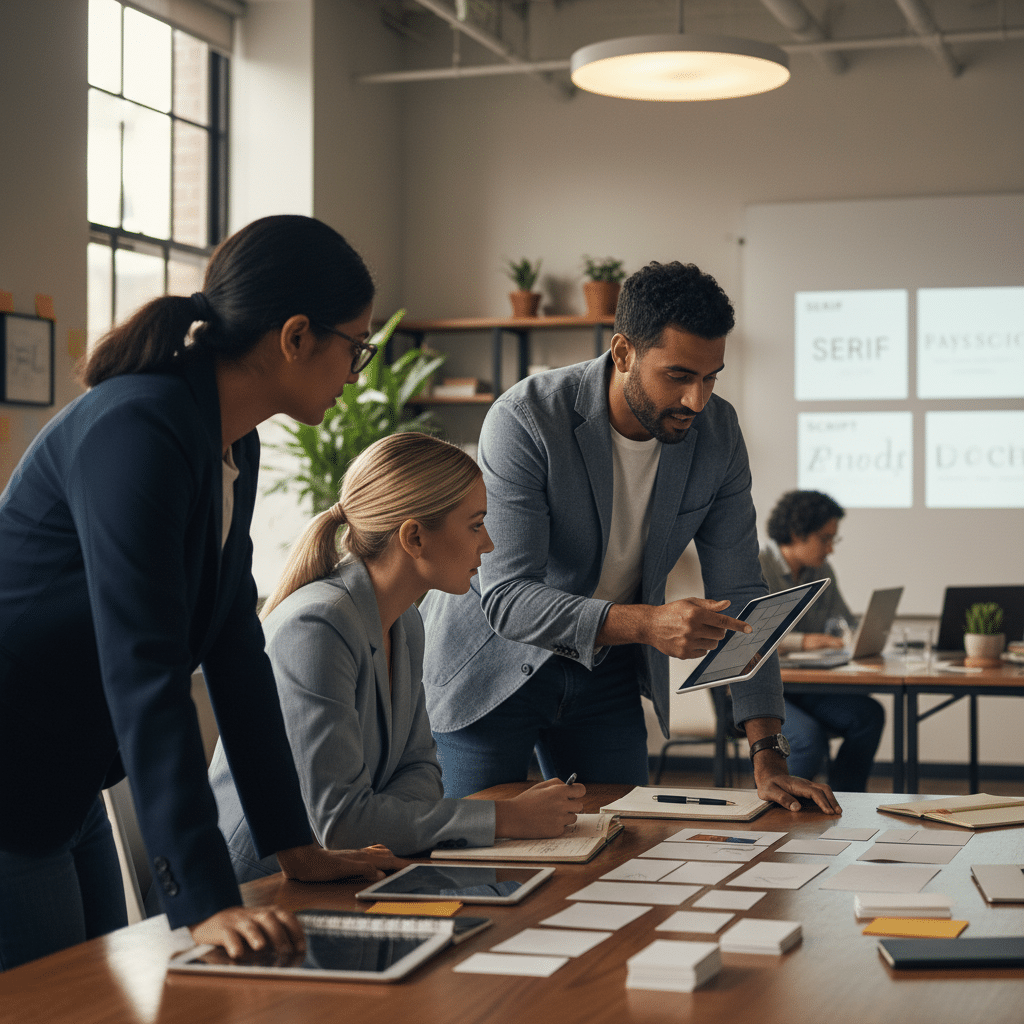
- ฟอนต์แต่ละประเภทสามารถกระตุ้นการรับรู้และอารมณ์ที่แตกต่างกัน เช่น ความน่าเชื่อถือ ความหรูหรา หรือความเป็นมิตร
- การเลือกฟอนต์ที่ไม่สอดคล้องกับบุคลิกของแบรนด์ อาจทำให้การสื่อสารคลาดเคลื่อน ลดความน่าเชื่อถือ และส่งผลเสียต่อภาพลักษณ์โดยรวม
- จิตวิทยาฟอนต์ (Font Psychology) คือการจับคู่คุณลักษณะของฟอนต์ให้เข้ากับเป้าหมายการสื่อสารของแบรนด์ เพื่อสร้างการจดจำและอิทธิพลต่อการตัดสินใจของผู้บริโภค
- ฟอนต์ถือเป็นองค์ประกอบสำคัญเทียบเท่ากับโลโก้และสีประจำแบรนด์ ซึ่งต้องมีความสม่ำเสมอในการใช้งานทุกช่องทาง
- การเลือกฟอนต์สำหรับธุรกิจ SME ควรคำนึงถึงความอ่านง่าย (Legibility) และความสามารถในการปรับใช้กับสื่อหลากหลายประเภท ตั้งแต่ฉลากสินค้าขนาดเล็กไปจนถึงป้ายโฆษณาขนาดใหญ่
ความหมายที่ซ่อนอยู่ในตัวอักษร
ในโลกของการตลาดและการสร้างแบรนด์ ทุกองค์ประกอบภาพล้วนมีความสำคัญในการสื่อสารไปยังผู้บริโภค ตั้งแต่สี โลโก้ ไปจนถึงสิ่งที่มักถูกมองข้ามอย่าง “ฟอนต์” หรือรูปแบบตัวอักษร แต่แท้จริงแล้ว ฟอนต์คือเครื่องมือทรงพลังที่สามารถกำหนดโทนและบุคลิกของแบรนด์ได้ทันทีที่ผู้คนมองเห็น การเลือกฟอนต์ที่เหมาะสมจึงไม่ใช่แค่เรื่องของความสวยงาม แต่เป็นศาสตร์และศิลป์ที่อิงหลักจิตวิทยาเพื่อสร้างการเชื่อมต่อทางอารมณ์กับลูกค้า
จิตวิทยาฟอนต์คืออะไรและเหตุใดจึงสำคัญต่อแบรนด์
นิยามของจิตวิทยาฟอนต์
จิตวิทยาฟอนต์ (Font Psychology) คือการศึกษาว่ารูปแบบตัวอักษรที่แตกต่างกันส่งผลต่อความคิด ความรู้สึก และการรับรู้ของผู้คนอย่างไร ในเชิงการตลาด นี่คือกระบวนการเลือกใช้ฟอนต์อย่างมีกลยุทธ์ เพื่อให้สอดคล้องกับบุคลิกภาพของแบรนด์ (Brand Personality) และกระตุ้นการตอบสนองที่ต้องการจากกลุ่มเป้าหมาย ไม่ว่าจะเป็นการสร้างความน่าเชื่อถือ ความรู้สึกหรูหรา ความเป็นมิตร หรือความทันสมัย
ฟอนต์ทำหน้าที่เป็นเหมือน “น้ำเสียง” ของแบรนด์ในรูปแบบภาพ แม้ว่าข้อความจะเหมือนกัน แต่การนำเสนอด้วยฟอนต์ที่ต่างกันสามารถเปลี่ยนการตีความของผู้รับสารได้อย่างสิ้นเชิง ตัวอย่างเช่น ฟอนต์ที่ดูสนุกสนานอาจไม่เหมาะกับสถาบันการเงินที่ต้องการความน่าเชื่อถือ ในทางกลับกัน ฟอนต์ที่ดูเป็นทางการเกินไปก็อาจทำให้แบรนด์สินค้าสำหรับเด็กดูไม่น่าเข้าถึง
พลังของฟอนต์ในการสื่อสารอัตลักษณ์แบรนด์
ฟอนต์เป็นส่วนหนึ่งของอัตลักษณ์แบรนด์ (Brand Identity) ที่มีความสำคัญไม่แพ้โลโก้หรือสี การเลือกฟอนต์ที่สอดคล้องกันในทุกสื่อ ไม่ว่าจะเป็นเว็บไซต์ บรรจุภัณฑ์ หรือสื่อสังคมออนไลน์ จะช่วยสร้างความแข็งแกร่งและการจดจำแบรนด์ได้ในระยะยาว งานวิจัยเชิงการตลาดบางชิ้นชี้ให้เห็นว่าฟอนต์บางประเภทสามารถเพิ่มการรับรู้ในคุณลักษณะบางอย่างของแบรนด์ได้จริง เช่น เพิ่มความน่าเชื่อถือ หรือสร้างความโดดเด่นในใจผู้บริโภคได้ในระดับที่วัดผลเป็นเปอร์เซ็นต์
การเลือกฟอนต์ที่ไม่สอดคล้องกับโทนของแบรนด์ อาจทำให้ผู้รับสารเกิดความสับสน ลดการมีส่วนร่วม และบั่นทอนความน่าเชื่อถือของแบรนด์ลงอย่างไม่น่าเชื่อ
ดังนั้น สำหรับผู้ประกอบการ SME การให้ความสำคัญกับการเลือกฟอนต์ตั้งแต่ขั้นตอนการออกแบบโลโก้ หรือออกแบบฉลากสินค้า จึงเป็นการลงทุนที่คุ้มค่าเพื่อสร้างรากฐานของแบรนด์ให้มั่นคง
ถอดรหัสบุคลิกภาพผ่านประเภทฟอนต์
การทำความเข้าใจประเภทของฟอนต์และบุคลิกภาพที่แต่ละประเภทสื่อออกมา จะช่วยให้การเลือกฟอนต์สำหรับสร้างแบรนด์เป็นไปอย่างแม่นยำและตรงเป้าหมายมากขึ้น โดยฟอนต์สามารถแบ่งออกเป็นกลุ่มหลักๆ ได้ดังนี้
| ประเภทฟอนต์ | บุคลิกภาพและการรับรู้ | เหมาะสำหรับแบรนด์ |
| Serif (มีเชิง) | เป็นทางการ, คลาสสิก, น่าเชื่อถือ, สง่างาม, มีประวัติศาสตร์ | สถาบันการเงิน, สำนักกฎหมาย, แบรนด์หรู, สินค้าที่มีประวัติยาวนาน, สื่อสิ่งพิมพ์, มหาวิทยาลัย |
| Sans-serif (ไม่มีเชิง) | ทันสมัย, เรียบง่าย, เป็นมิตร, เข้าถึงง่าย, ชัดเจน | บริษัทเทคโนโลยี, สตาร์ทอัพ, แบรนด์แฟชั่นสมัยใหม่, ธุรกิจบริการที่เน้นความรวดเร็ว, แอปพลิเคชัน |
| Script (ลายมือ) | หรูหรา, อ่อนหวาน, เป็นส่วนตัว, สร้างสรรค์, โรแมนติก | การ์ดเชิญ, แบรนด์เครื่องสำอาง, ร้านขนม, ร้านอาหาร fine-dining, สินค้าแฮนด์เมด |
| Display / Decorative | สนุกสนาน, มีเอกลักษณ์เฉพาะตัวสูง, ดึงดูดสายตา, ตามสมัยนิยม | โลโก้, หัวข้อโปสเตอร์, แบรนด์สินค้าสำหรับเด็ก, อีเวนต์พิเศษ, สินค้าตามฤดูกาล |
Serif: ความคลาสสิกและความน่าเชื่อถือ
ฟอนต์ประเภท Serif หรือฟอนต์ “มีเชิง” คือฟอนต์ที่มีขีดเล็กๆ ประดับอยู่ที่ปลายตัวอักษร เป็นรูปแบบฟอนต์ที่มีมาแต่ดั้งเดิม ให้ความรู้สึกถึงความมั่นคง, ประวัติศาสตร์, และความน่าเชื่อถือ จึงมักถูกเลือกใช้โดยแบรนด์ที่ต้องการสร้างภาพลักษณ์ที่ดูเป็นทางการและทรงเกียรติ เช่น สถาบันการเงิน, หนังสือพิมพ์, หรือแบรนด์สินค้าหรูหรา
Sans-serif: ความทันสมัยและความเป็นมิตร
“Sans” ในภาษาฝรั่งเศสแปลว่า “ไม่มี” ดังนั้น Sans-serif จึงหมายถึงฟอนต์ที่ “ไม่มีเชิง” ที่ปลายตัวอักษร ทำให้ดูเรียบง่าย, สะอาดตา, และทันสมัย ฟอนต์กลุ่มนี้ได้รับความนิยมอย่างสูงในยุคดิจิทัลเนื่องจากอ่านง่ายบนหน้าจอคอมพิวเตอร์และมือถือ แบรนด์เทคโนโลยี, สตาร์ทอัพ, และธุรกิจที่ต้องการสื่อสารความเรียบง่ายและเป็นมิตรมักจะเลือกใช้ฟอนต์ประเภทนี้ ฟอนต์ Sans-serif ยังสามารถแบ่งย่อยได้อีก เช่น:
- Humanist Sans: ให้ความรู้สึกเป็นกันเองและจริงใจ มีความโค้งมนคล้ายลายมือมนุษย์
- Geometric Sans: สร้างจากรูปทรงเรขาคณิตพื้นฐาน ทำให้ดูเที่ยงตรงและทันสมัย
- Grotesque: เป็นฟอนต์ Sans-serif ยุคแรกๆ ที่มีความคลาสสิกร่วมสมัย ให้ความรู้สึกเรียบง่ายแต่ทรงพลัง
Script & Display: อารมณ์ความรู้สึกและความเฉพาะตัว
ฟอนต์ประเภท Script เลียนแบบลายมือเขียน ให้ความรู้สึกเป็นส่วนตัว, อ่อนหวาน, และหรูหรา เหมาะสำหรับแบรนด์ที่ต้องการเน้นอารมณ์ความรู้สึก เช่น ร้านดอกไม้, การ์ดแต่งงาน, หรือแบรนด์เครื่องสำอาง ส่วนฟอนต์ Display หรือ Decorative เป็นฟอนต์ที่ถูกออกแบบมาให้มีเอกลักษณ์โดดเด่นเพื่อดึงดูดสายตาโดยเฉพาะ มักใช้สำหรับหัวข้อใหญ่ๆ หรือโลโก้ แต่ไม่เหมาะกับเนื้อหาขนาดยาวเพราะอ่านค่อนข้างยาก การใช้ฟอนต์กลุ่มนี้ต้องระมัดระวัง เพราะหากใช้ผิดบริบทอาจทำให้แบรนด์ดูไม่เป็นมืออาชีพได้
แนวทางปฏิบัติในการเลือกฟอนต์เพื่อสร้างแบรนด์ให้แข็งแกร่ง
การเลือกฟอนต์ไม่ใช่การสุ่มเลือกตามความชอบส่วนตัว แต่เป็นกระบวนการที่ต้องวางแผนอย่างเป็นระบบเพื่อให้ได้ผลลัพธ์ที่ดีที่สุด นี่คือแนวทางปฏิบัติที่สามารถนำไปปรับใช้ได้
1. กำหนดเป้าหมายและบุคลิกของแบรนด์ให้ชัดเจน
ก่อนจะเลือกฟอนต์ ต้องตอบคำถามสำคัญเกี่ยวกับแบรนด์ให้ได้ก่อน เช่น แบรนด์ต้องการสื่อสารอะไร? (ความน่าเชื่อถือ, ความสนุกสนาน, ความหรูหรา) กลุ่มเป้าหมายคือใคร? บุคลิกของแบรนด์เป็นอย่างไร? (จริงจัง, เป็นกันเอง, ทันสมัย) เมื่อมีภาพที่ชัดเจนแล้ว การเลือกประเภทฟอนต์ที่สอดคล้องกับบุคลิกเหล่านั้นจะทำได้ง่ายขึ้น
2. คำนึงถึงความอ่านง่ายและการใช้งานในหลายแพลตฟอร์ม
ความสวยงามต้องมาพร้อมกับประโยชน์ใช้สอย ฟอนต์ที่เลือกต้องอ่านง่าย (Legible) ในทุกขนาด ไม่ว่าจะอยู่บนฉลากสินค้าชิ้นเล็กๆ, เมนูอาหาร, เว็บไซต์บนมือถือ, หรือป้ายโฆษณาขนาดใหญ่ ควรทดสอบฟอนต์ในสถานการณ์การใช้งานจริงเพื่อให้แน่ใจว่าข้อความยังคงสื่อสารได้อย่างชัดเจน
3. จำกัดจำนวนฟอนต์เพื่อสร้างความสม่ำเสมอ
การใช้ฟอนต์มากเกินไปจะทำให้ภาพลักษณ์ของแบรนด์ดูสับสนและไม่เป็นมืออาชีพ โดยทั่วไปแล้ว การใช้ฟอนต์หลักเพียง 2-3 ครอบครัว (Font Family) ก็เพียงพอแล้ว โดยอาจกำหนดให้มีฟอนต์สำหรับหัวข้อหลัก (Heading), ฟอนต์สำหรับเนื้อหา (Body Text), และฟอนต์สำหรับเน้นข้อความ (Accent) เพื่อสร้างลำดับชั้นของข้อมูลที่ชัดเจนและเป็นระเบียบ
4. ทดสอบกับกลุ่มเป้าหมายจริง
แม้จะมีทฤษฎีรองรับ แต่การรับรู้ของคนอาจแตกต่างกันไป วิธีที่ดีที่สุดคือการนำฟอนต์ที่เลือกไปทดสอบกับกลุ่มลูกค้าเป้าหมาย อาจทำในรูปแบบ A/B Testing (เปรียบเทียบดีไซน์ 2 แบบที่ใช้ฟอนต์ต่างกัน) หรือทำแบบสำรวจง่ายๆ เพื่อดูว่าฟอนต์นั้นสามารถสื่อสารบุคลิกและอารมณ์ของแบรนด์ได้ตามที่ตั้งใจไว้หรือไม่
ข้อควรระวัง: กับดักที่อาจทำลายภาพลักษณ์แบรนด์
แม้การเลือกฟอนต์จะมีประโยชน์มหาศาล แต่ก็มีความเสี่ยงหากเลือกผิดพลาด ข้อควรระวังที่สำคัญคือการใช้ฟอนต์ตกแต่ง (Decorative/Display) ในบริบทที่ไม่เหมาะสม เช่น การใช้ฟอนต์ที่ดูสนุกสนานสำหรับเอกสารทางกฎหมายหรือประกาศสำคัญ ซึ่งอาจทำให้เนื้อหาขาดความน่าเชื่อถือ นอกจากนี้ การใช้ฟอนต์ที่อ่านยากเกินไปสำหรับเนื้อหาหลักก็เป็นข้อผิดพลาดร้ายแรง เพราะจะสร้างประสบการณ์ที่ไม่ดีแก่ผู้ใช้ และทำให้พวกเขาออกจากเว็บไซต์หรือเพิกเฉยต่อสื่อสิ่งพิมพ์นั้นๆ ไปในที่สุด
บทสรุป: ฟอนต์ไม่ใช่แค่ตัวอักษร แต่คือเสียงของแบรนด์
สรุปได้ว่า การเลือกฟอนต์เป็นองค์ประกอบเชิงกลยุทธ์ที่ส่งผลโดยตรงต่อการรับรู้แบรนด์ ไม่ว่าจะเป็นธุรกิจขนาดใหญ่หรือผู้ประกอบการ SME การทำความเข้าใจในหลัก จิตวิทยาฟอนต์ จะช่วยให้สามารถเลือกใช้ตัวอักษรเพื่อสื่อสารบุคลิกภาพ, สร้างความน่าเชื่อถือ, และสร้างความสัมพันธ์ทางอารมณ์กับลูกค้าได้อย่างมีประสิทธิภาพ ฟอนต์ไม่ได้เป็นเพียงแค่ส่วนประกอบด้านความสวยงามในการออกแบบโลโก้หรือออกแบบฉลากสินค้า แต่เป็นเสียงที่มองเห็นได้ซึ่งจะบอกเล่าเรื่องราวของแบรนด์และสร้างการจดจำที่ยั่งยืนในใจของผู้บริโภค